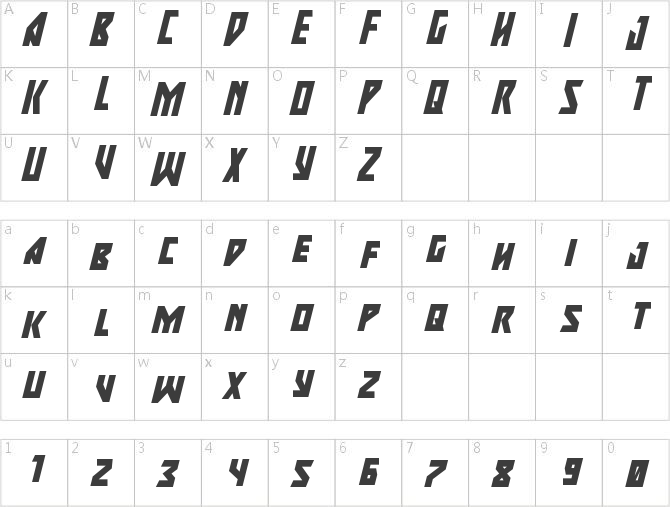
Major Force Super-Italic 詳情頁
Major Force Super-Italic
Major Force Super-Italic字體字庫是一款讓人賞心悅目、百看不厭的英文字體,適合各類廣告和產(chǎn)品包裝設計應用,字體大小0.02MB,格式為ttf字體,上傳用戶是釜源貿(mào)易,作者/版權方為未知